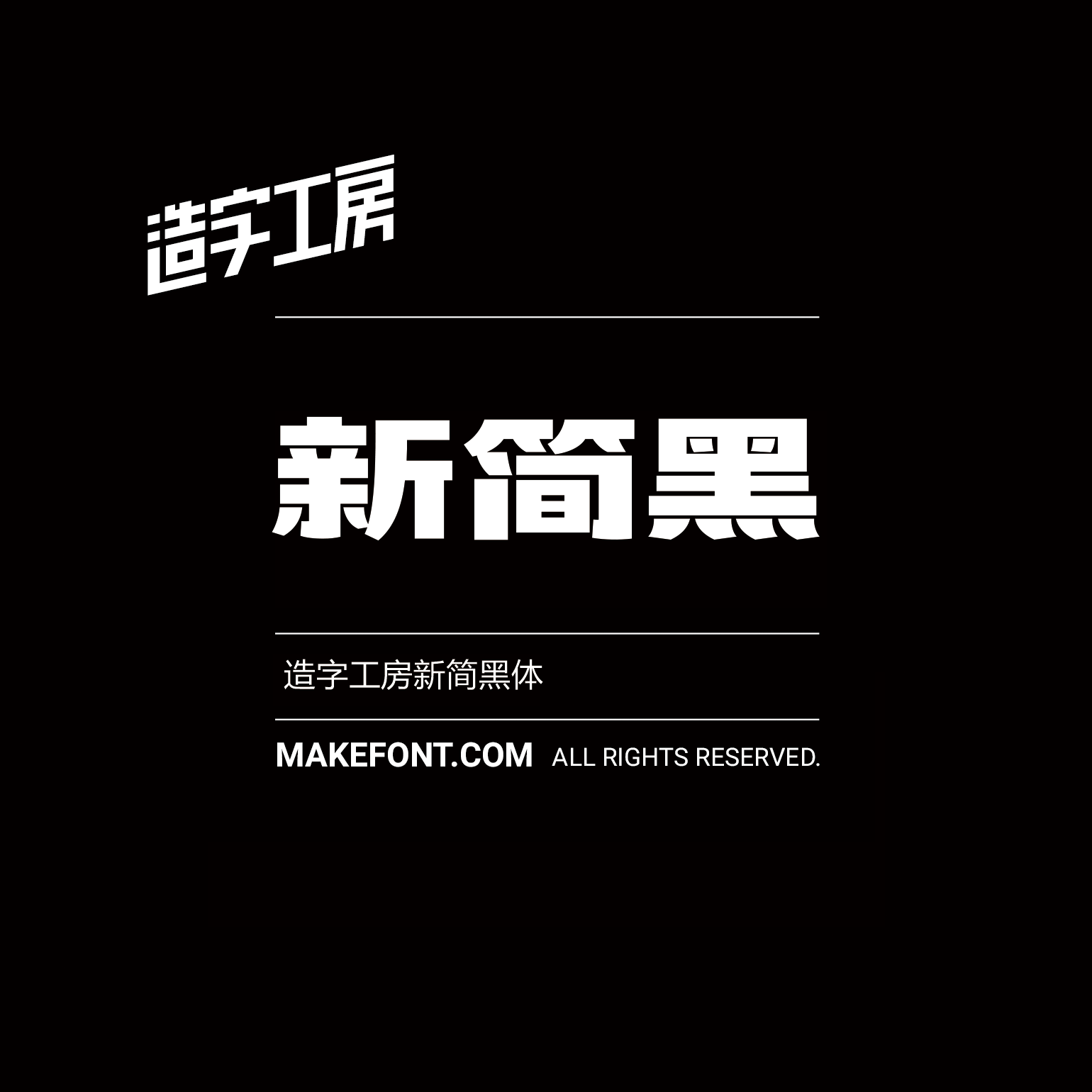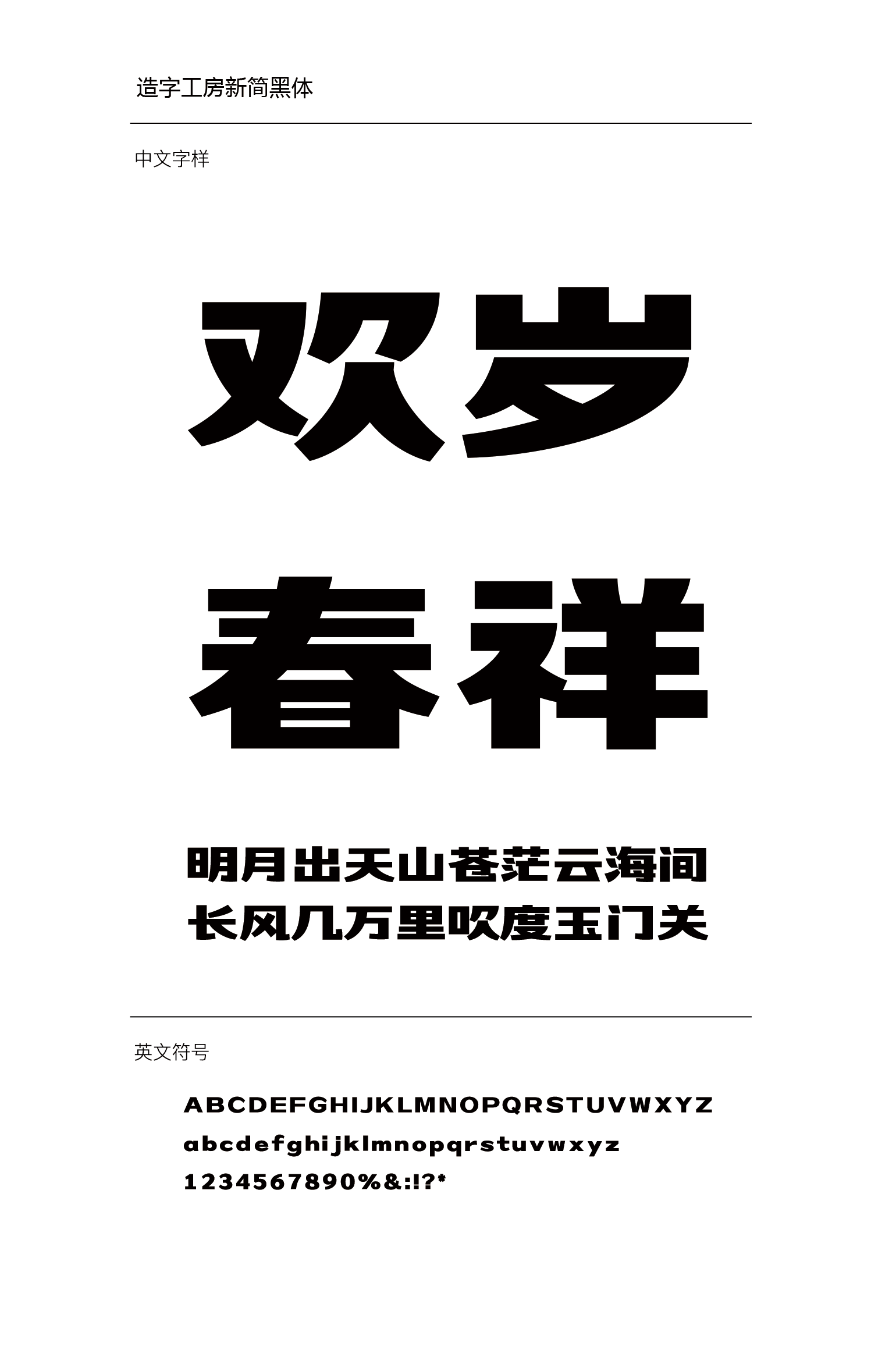
造字工房新简黑体设计说明
造字工房新简黑体以扁平化字形与饱满结构为核心设计,笔触厚重且棱角锐利,在起笔顿挫与收笔截断的对比中形成独特张力。通过立体切削般的边缘处理注入未来科技感,严谨的字形架构中透露出先锋态度。字体凭借高识别度的硬朗风格,成为广告标牌、品牌视觉、艺术创作等领域提升视觉冲击力的优质选择。本字体为简体字库,采用OpenType/CID格式,Adobe-GB1-5编码。基于中华人民共和国GB2312-80字符集标准,另按需添加101个汉字。共收容字数6864CJK汉字,ASCII常用字符100个。